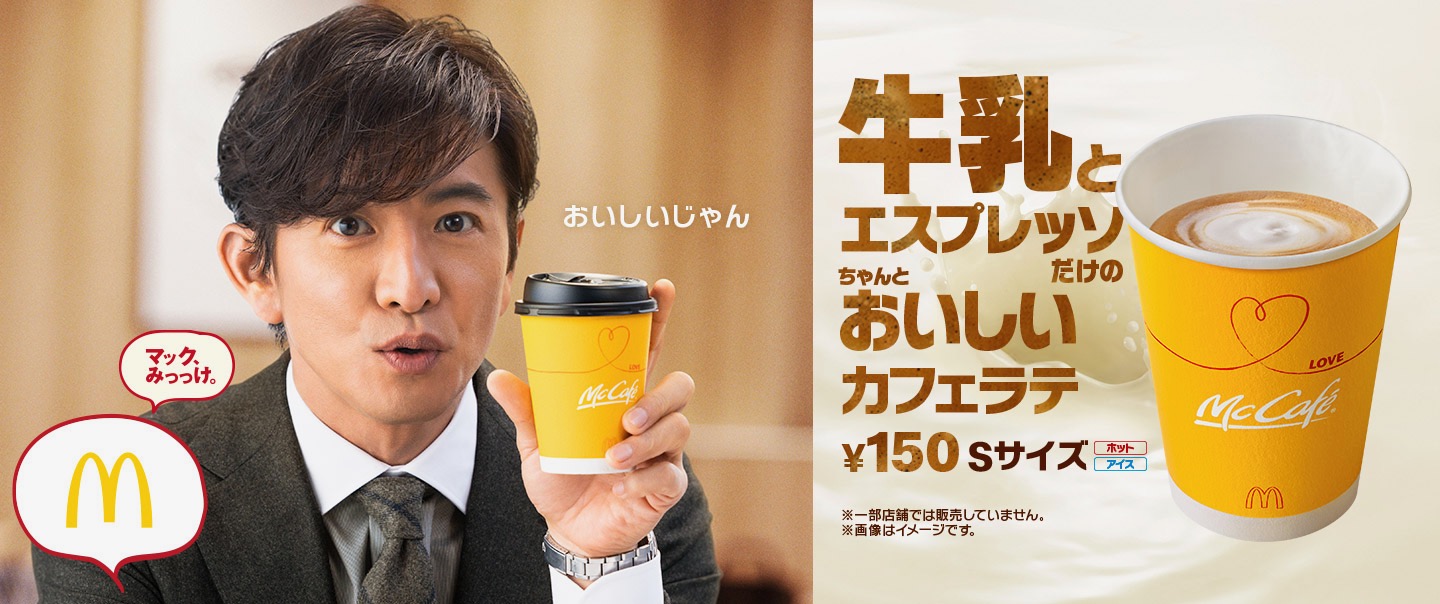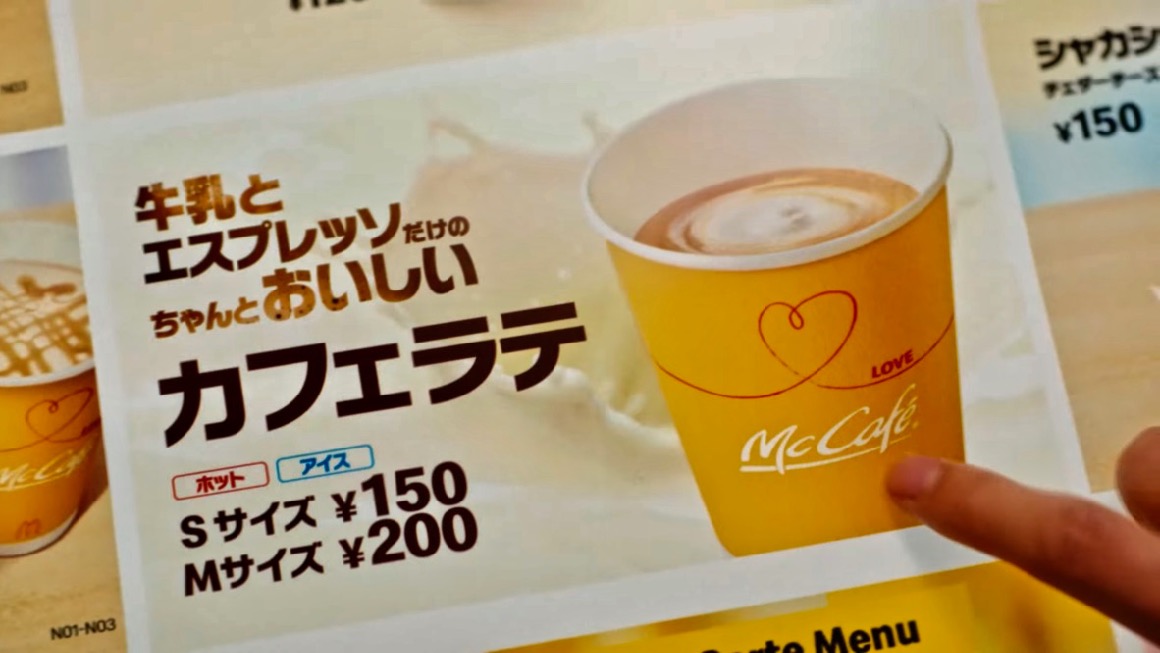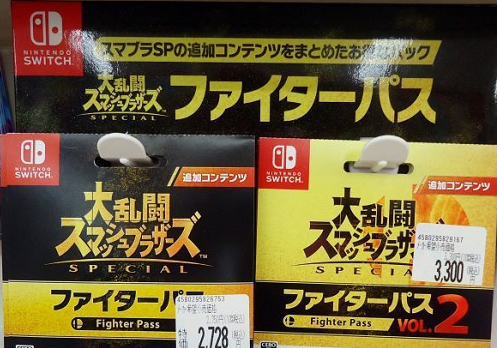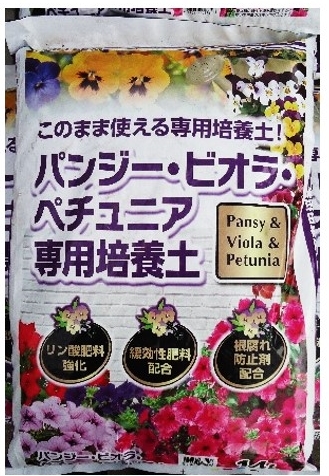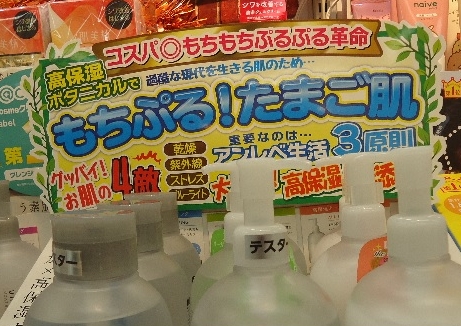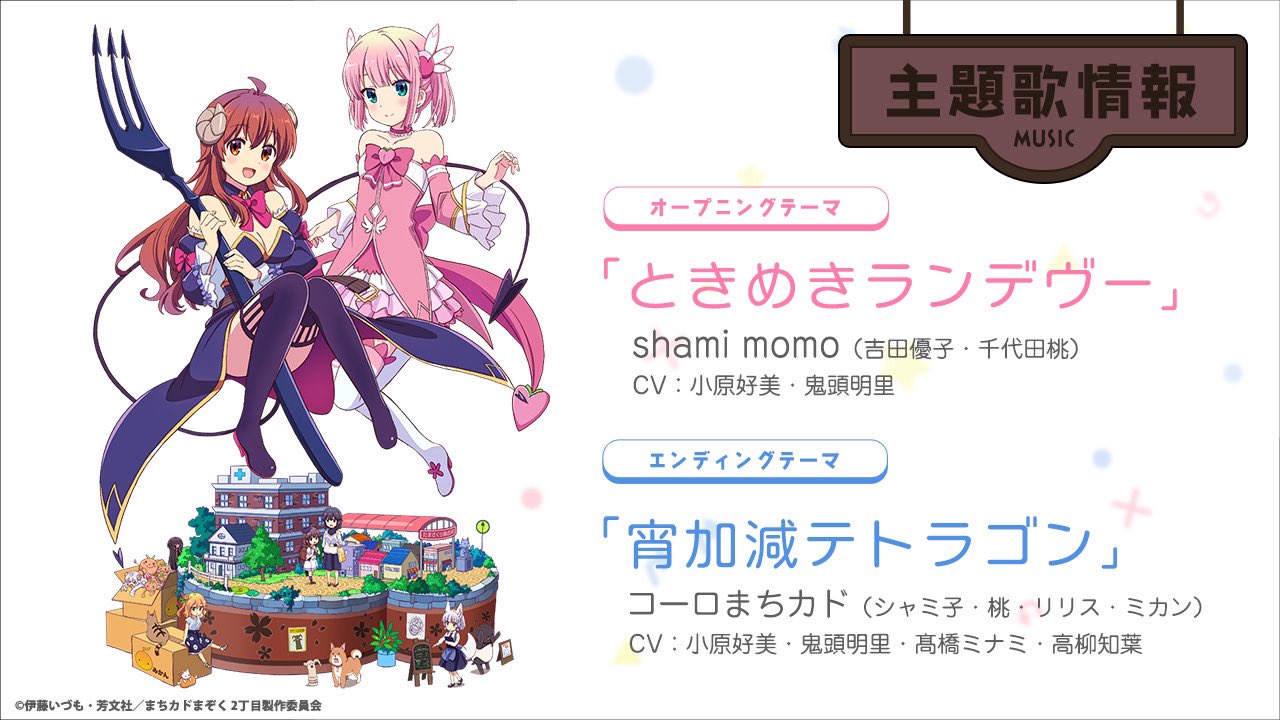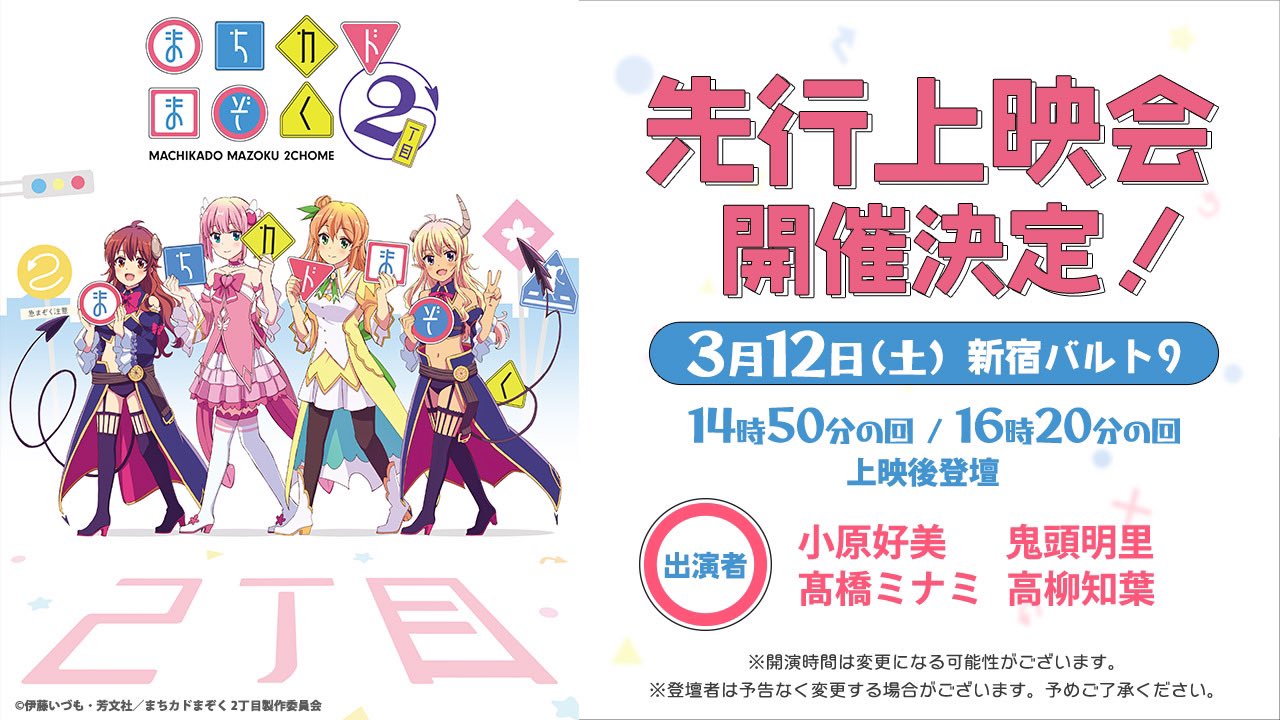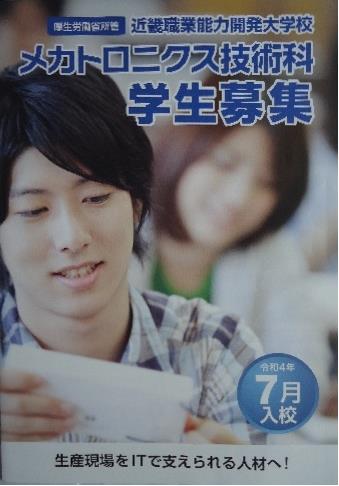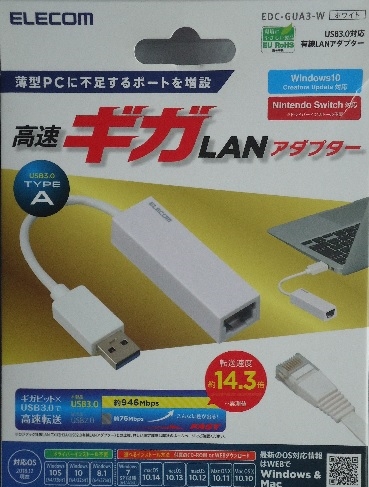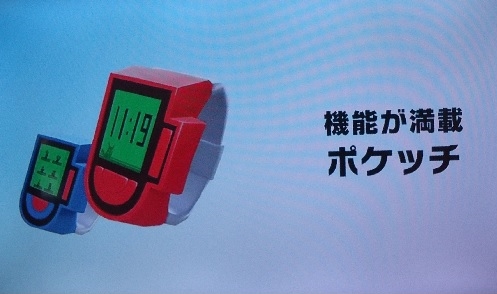
新聞広告 さとうゆたか
今朝の読売新聞。
国立新美術館のダミアン・ハースト展。
縦画の「音引き」と「ト」には手が加えられている。
こちらはポスター。
ポップ 大阪のうめ吉
衣料・日用品店のポップ
大阪市平野区
案内板 大阪のうめ吉
案内板
大阪府八尾市の
ショッピングモール・リノアス
テレビ番組 さとうゆたか
ABEMAテレビだったかも…。
これも…。
ニタラゴルイカ ゆう
少し前の急上昇から。
LaQ 大阪のうめ吉
LaQカプセルトイシリーズ
ショッピングセンター玩具売り場で
ガンダム 大阪のうめ吉
ストライクガンダム
発売 バンダイ
大阪府松原市のショッピングモールテナントで
ゲーム機 大阪のうめ吉
ゲーム機
ショッピングセンターゲームコーナーで
ひろゆきの切り抜き 匿名
ニタラゴルイカが使用されています。
「論」の字をみれば、ニタラゴルイカとはっきり判りますね。
ポスター 大阪のうめ吉
ドンブラスターのポスター
大阪市阿倍野区の近鉄百貨店で